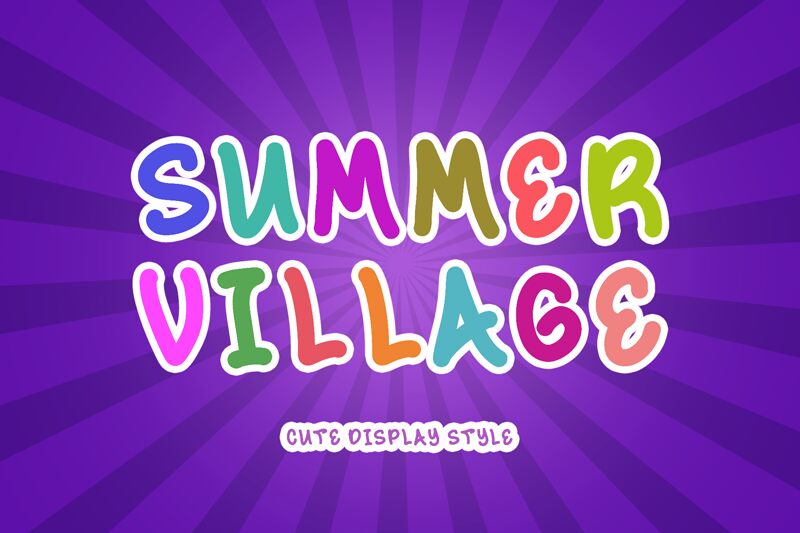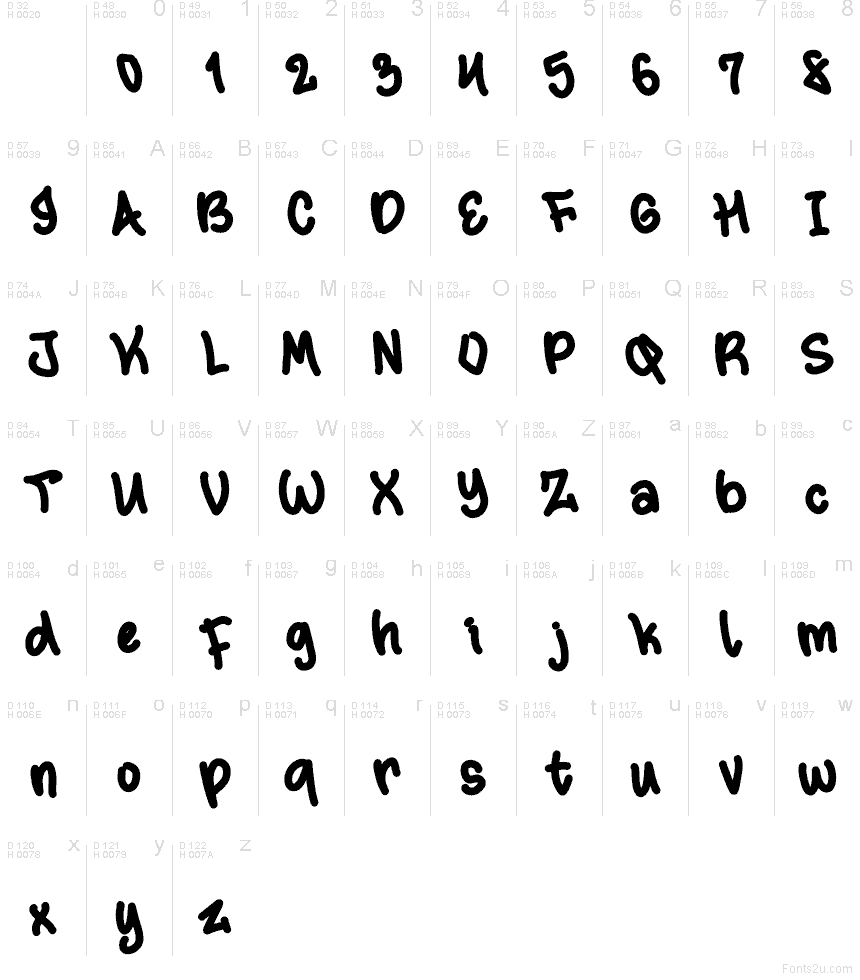
Summer Village Demo
Summer Village é uma fonte estilo comic gratuita, com letras arredondadas de aparência desenhada à mão e curvas suaves e irregulares, que dão às palavras um toque casual de caderno de esboços. As suas laçadas amplas e ritmo fechado mantêm-na amigável e informal, sem parecer rígida.
Summer Village é uma fonte gratuita que funciona muito bem em cartazes de eventos de verão, marcas infantis, menus de cafés, gráficos para redes sociais e embalagens alegres, pois as suas formas arredondadas e soltas transmitem proximidade e personalidade. Também se adequa a títulos de revistas, cartões de felicitações e textos curtos de logótipos quando procura um toque manuscrito caloroso, em vez de um estilo de exibição formal.